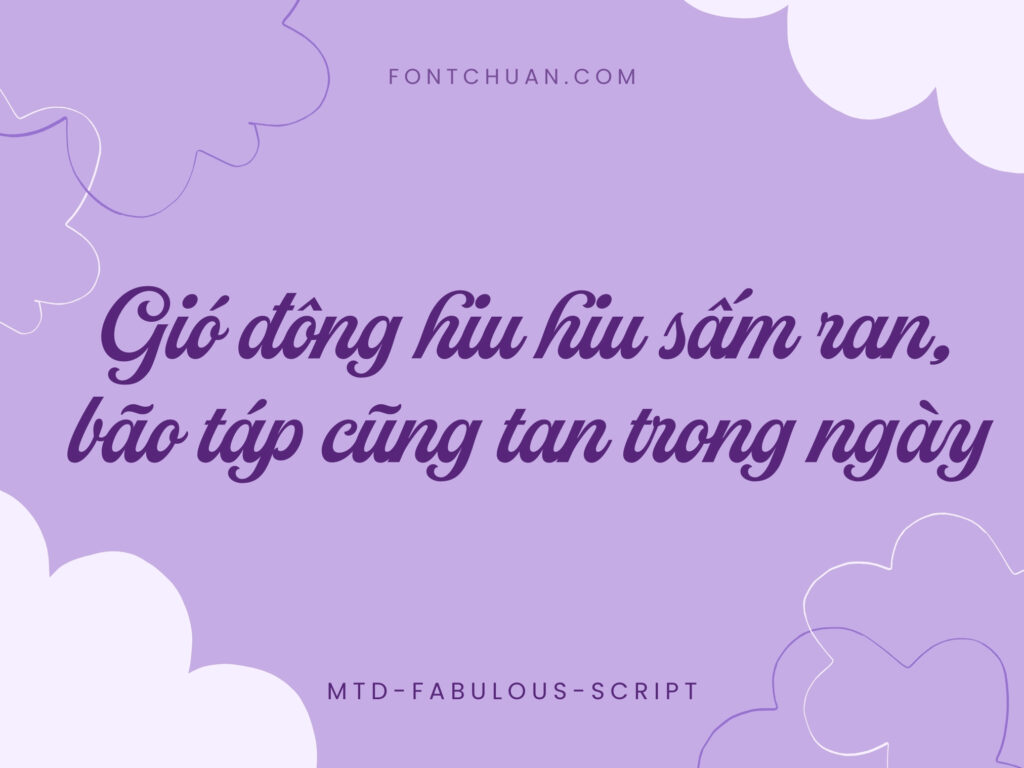
Font MTD Fabulous Script Việt Hóa
Font MTD Fabulous Script là một phông chữ viết tay hiện đại, được thiết kế bởi Stripes Studio và phát hành trên các nền tảng font trực tuyến. Font đã được Việt hóa bởi Mộc Hạ, hỗ trợ tiếng Việt và hơn 90 ngôn ngữ khác, giúp mở rộng khả năng ứng dụng trong các thiết kế đa ngôn ngữ. Đây là một trong những phông chữ được cộng đồng thiết kế đánh giá cao và ứng dụng trong nhiều dự án sáng tạo, đáp ứng nhu cầu đa dạng của người dùng.
MTD Fabulous Script nổi bật với các đường nét mềm mại, uyển chuyển và tự nhiên, mang đến cảm giác thân thiện và gần gũi. Font rất phù hợp cho các thiết kế logo, thương hiệu cá nhân, thiệp mời, tiêu đề, bao bì sản phẩm và các ấn phẩm đòi hỏi sự tinh tế và cá nhân hóa. Các ngành nghề phù hợp bao gồm quảng cáo, giáo dục, công nghệ, thiệp cưới và ảnh cưới. Font này cũng lý tưởng cho các sự kiện như Tết, Giáng sinh, Valentine và các lễ hội khác.